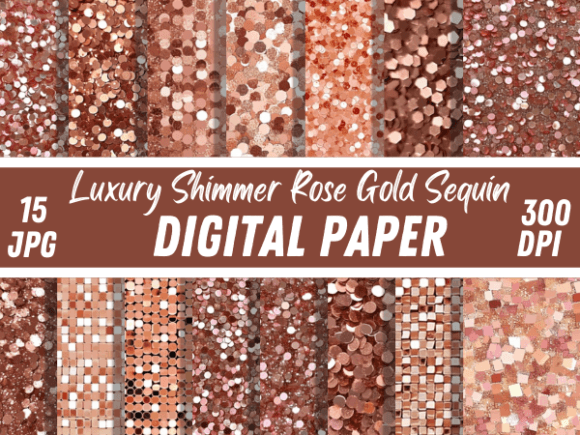
Luxury Shimmer Glitter Rose Gold Sequin
Việc tìm kiếm các thành phần thiết kế phù hợp có thể là một thách thức, nhưng Luxury Shimmer Glitter Rose Gold Sequin cung cấp một bộ sưu tập đặc biệt giúp nâng tầm công việc của bạn ngay lập tức.
Cho dù bạn đang tạo sản phẩm POD (In theo yêu cầu), thiệp mời đám cưới hay đồ họa mạng xã hội, Luxury Shimmer Glitter Rose Gold Sequin đều là một sự lựa chọn lý tưởng.